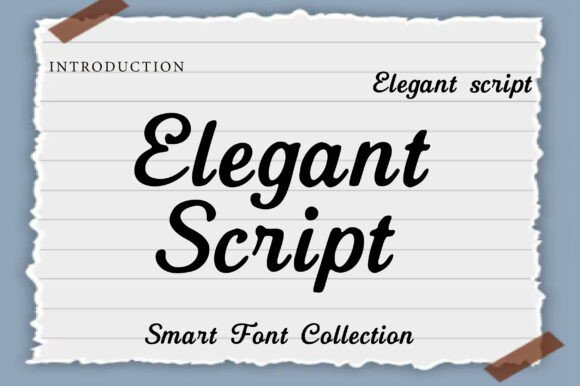
Elegant Script
หากคุณกำลังมองหาเนื้อหาคุณภาพสูงเช่น Elegant Script แพ็คเกจพรีเมียมนี้เป็นตัวเลือกที่ยอดเยี่ยมสำหรับโปรเจ็กต์สร้างสรรค์ของคุณ
สร้างขึ้นอย่างแม่นยำ Elegant Script ให้เวกเตอร์ที่สะอาด พิมพ์ตัวอักษรที่ราบรื่น และใบอนุญาตเชิงพาณิชย์เพื่อความสบายใจ